싸인을 만들 때 유명인의 싸인을 참고하면 많은 도움이 돼요. 그들의 싸인은 단순한 이름이 아니라 브랜드, 권위, 개성을 담고 있기 때문이에요. ✍️
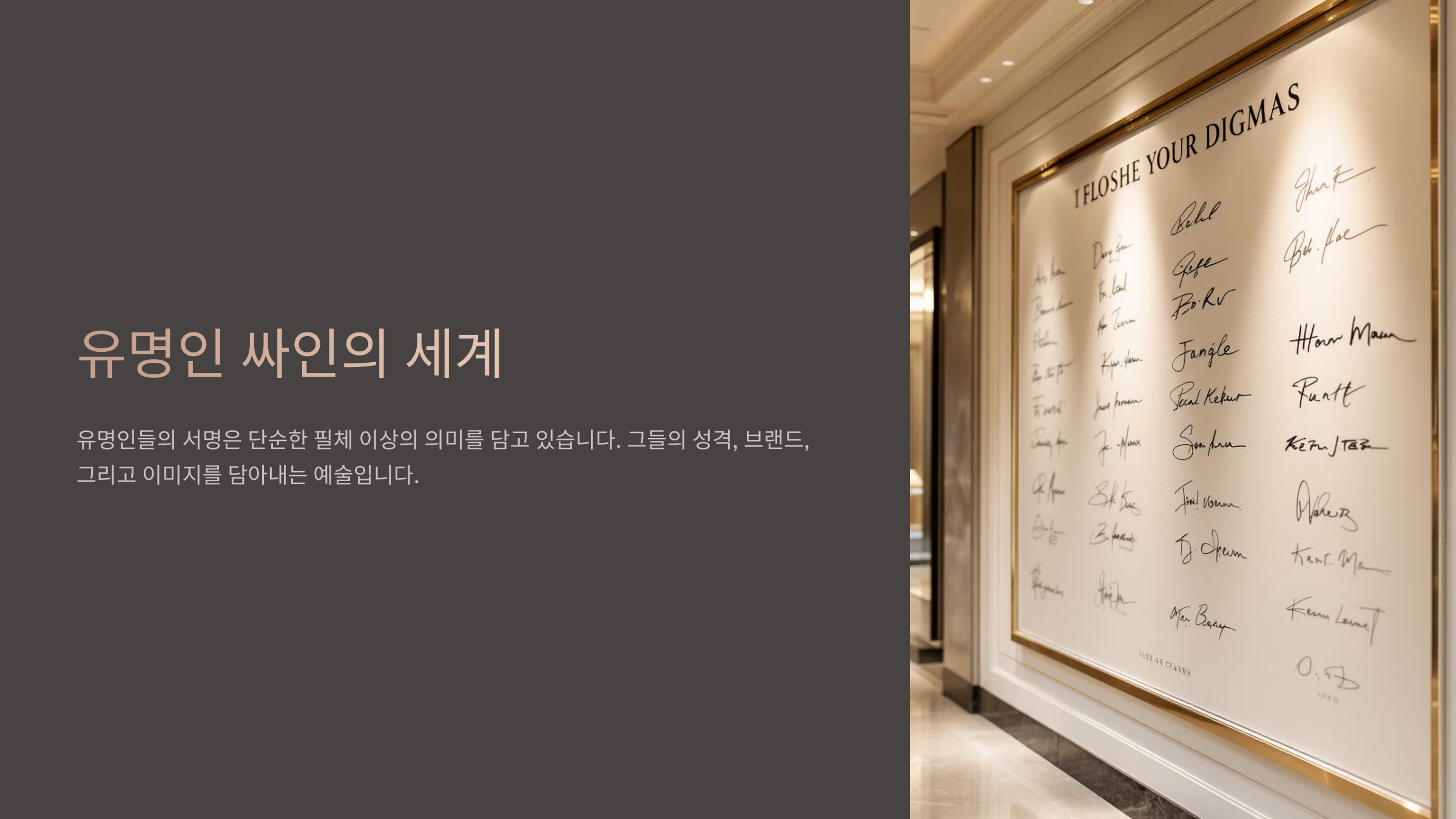
예를 들어, 빌 게이츠, 스티브 잡스, 일론 머스크 같은 CEO들의 싸인은 비즈니스적인 신뢰감을 주고, 유명 연예인들의 싸인은 개성 넘치는 스타일을 보여줘요. 이제 유명인들의 싸인을 분석하고, 나만의 스타일을 만드는 방법을 알아볼까요? 🔥
유명인 싸인을 참고하는 이유 🌟
유명인의 싸인은 단순한 서명이 아니라 그들의 브랜드와 개성을 담고 있는 요소예요. 그렇기 때문에 싸인을 연구하면 멋진 스타일을 만들고, 나만의 개성을 살릴 수 있어요! ✍️유명인의 싸인을 참고하는 이유는 다음과 같아요:
📌 유명인 싸인 참고의 장점 ✅
이유 설명 1. 개성 표현 유명인의 싸인은 강한 인상을 주는 요소가 많음 2. 브랜드 이미지 구축 CEO나 연예인의 싸인은 브랜드와 연결됨 3. 필기체 연구 다양한 필기체 스타일을 배울 수 있음 4. 간결함과 가독성 읽기 쉬우면서도 멋진 싸인 제작 가능 유명인의 싸인을 보면 싸인의 흐름, 스타일, 개성을 배울 수 있어요! 그럼 이제, 유명 CEO들의 싸인 스타일을 분석해 볼까요? 💼
유명 CEO들의 싸인 스타일 💼
세계적인 기업 CEO들의 싸인은 비즈니스적 신뢰감과 권위를 나타내는 요소예요. 그들의 싸인을 분석하면 깔끔하고 프로페셔널한 싸인 스타일을 배울 수 있어요! ✍️
📌 유명 CEO 싸인 스타일 분석 ✅
CEO 싸인 특징 스타일 빌 게이츠 (Bill Gates) 이니셜을 강조하며 깔끔한 필기체 "B. Gates" 스티브 잡스 (Steve Jobs) 독특한 필체와 흐름이 있는 곡선 "Steve Jobs" (곡선 강조) 일론 머스크 (Elon Musk) 빠르고 역동적인 스타일 "E. Musk" (속도감 강조) 제프 베이조스 (Jeff Bezos) 부드러운 필기체로 자연스러운 흐름 "J. Bezos" CEO들의 싸인은 명확하고 깔끔하면서도, 속도감과 개성이 반영된 스타일이 많아요. 그럼 이제, 연예인과 스포츠 스타들의 싸인은 어떤 특징이 있는지 살펴볼까요? 🎤⚽
연예인과 스포츠 스타들의 싸인 특징 🎤⚽
연예인과 스포츠 스타들의 싸인은 팬들에게 강한 인상을 남기고, 브랜드 이미지를 형성하는 요소예요. 이들의 싸인은 개성이 강하고 예술적인 느낌이 많으며, 종종 독창적인 심볼이 포함되기도 해요. ✍️
📌 유명 연예인 & 스포츠 스타 싸인 스타일 ✅
유명인 싸인 특징 스타일 마이클 잭슨 (Michael Jackson) 길게 늘어진 곡선과 리드미컬한 흐름 "M. Jackson" (유연한 곡선 강조) 비욘세 (Beyoncé) 스타일리시한 필기체와 끝에 별 장식 "Beyoncé ✨" 리오넬 메시 (Lionel Messi) 짧고 강렬한 획, 간결한 이니셜 "L. Messi" 크리스티아누 호날두 (Cristiano Ronaldo) 속도감 있는 강렬한 획과 강조된 C.R "C.Ronaldo ⚡" 연예인과 스포츠 스타들은 팬들에게 각인될 수 있도록 독창적이고 강한 스타일을 많이 사용해요. 그럼 이제, 정치인과 역사적 인물들의 싸인은 어떤 특징이 있는지 분석해볼까요? 🏛️
정치인과 역사적 인물의 싸인 분석 🏛️
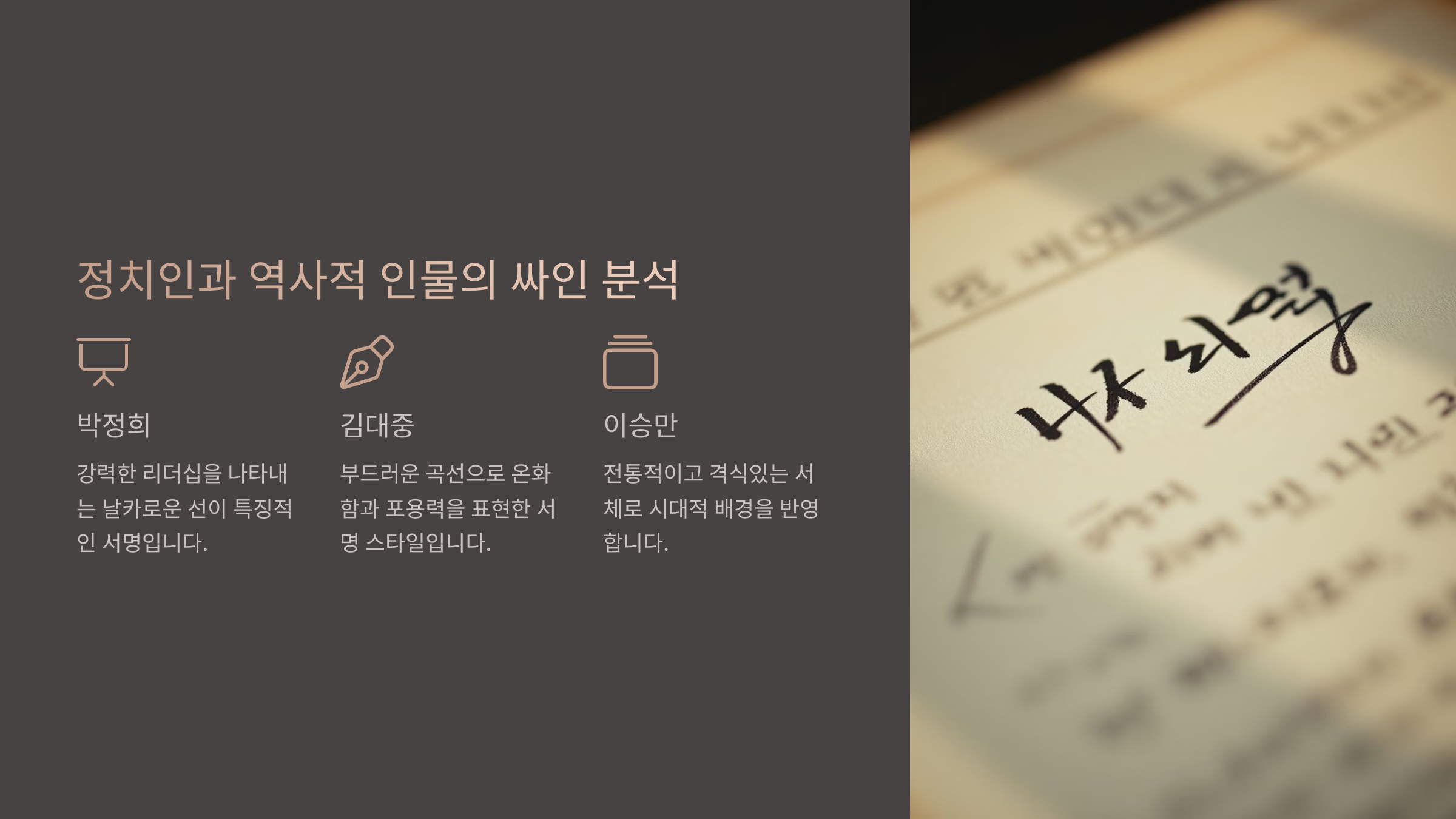
정치인과 역사적 인물들의 싸인은 권위, 신뢰, 리더십을 상징하는 요소예요. 이들의 싸인은 종종 강한 필압과 명확한 획이 특징이며, 공식 문서에서 많이 사용되죠. ✍️
📌 유명 정치인 & 역사적 인물의 싸인 스타일 ✅
인물 싸인 특징 스타일 조지 워싱턴 (George Washington) 정확하고 대칭적인 글씨체, 강한 필압 "G. Washington" 윈스턴 처칠 (Winston Churchill) 유려한 곡선과 독특한 필기체 "W. Churchill" 존 F. 케네디 (John F. Kennedy) 빠르고 자연스러운 흐름, 가독성 높은 필체 "J.F.K." 넬슨 만델라 (Nelson Mandela) 부드럽고 자연스러운 필기체, 연결된 획 "N. Mandela" 정치인과 역사적 인물들의 싸인은 위엄과 권위를 강조하는 요소가 많아요. 그럼 이제, 유명인의 싸인에서 우리가 배울 점을 정리해볼까요? ✨
유명인 싸인에서 배울 점 ✨
유명인의 싸인을 분석하면 어떤 요소가 멋진 싸인을 만드는지 배울 수 있어요. 단순히 따라 하는 것이 아니라, 핵심적인 스타일을 참고해 나만의 싸인을 만들어야 해요! ✍️
📌 유명인 싸인의 핵심 요소 ✅
요소 설명 예시 1. 간결함 읽기 쉽고 빠르게 쓸 수 있도록 단순한 스타일 유지 "J.K." / "H. Park" 2. 독창성 이름의 특정 글자를 강조하거나 특수 기호 활용 "M. Lee ✨" / "S. Lim ★" 3. 흐름 끊기지 않고 부드럽게 이어지는 필기체 활용 "Beyoncé" (유려한 곡선) 4. 속도감 빠르게 쓰면서도 형태가 유지되는 스타일 "E. Musk" (강한 획) 이제 유명인의 싸인에서 배운 요소들을 활용해 나만의 싸인 스타일을 만들어볼 차례예요! 🔥
나만의 싸인 스타일 만들기 ✍️
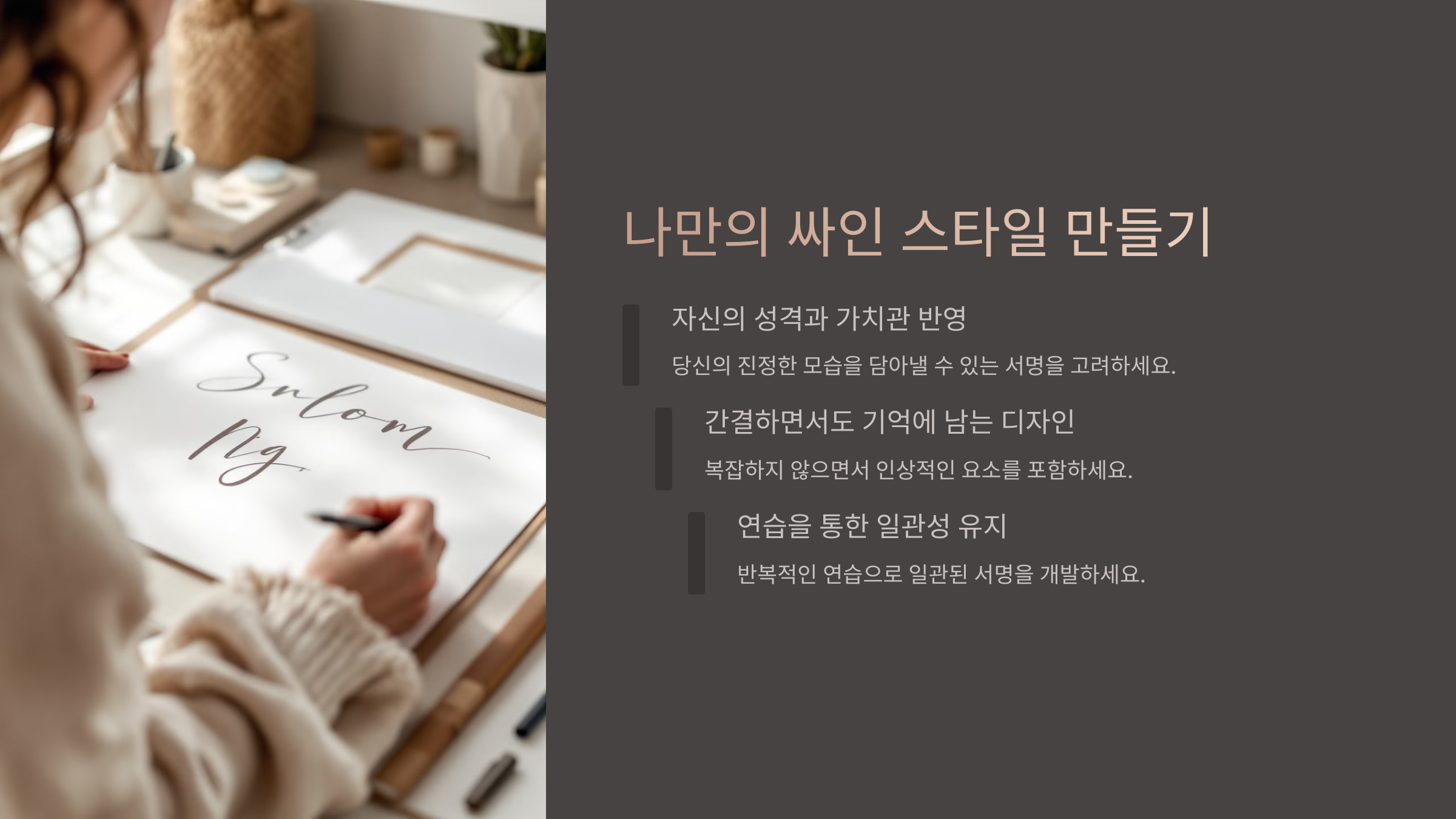
유명인의 싸인을 참고했다면, 이제 나만의 개성을 담은 싸인을 만들어볼 차례예요. 단순히 따라 하는 것이 아니라, 자신의 이름과 스타일을 반영해야 해요. ✅
📌 나만의 싸인 스타일을 만드는 5단계 🚀
단계 설명 1. 기본 형태 정하기 이름을 풀네임으로 쓸지, 이니셜을 활용할지 결정 2. 필기체 스타일 선택 부드러운 곡선, 직선, 속도감 있는 획 중 선택 3. 디테일 추가 밑줄, 점, 별 등 자신만의 개성을 더할 요소 정하기 4. 반복 연습 적어도 100번 이상 싸인을 연습하며 손에 익히기 5. 실전 적용 계약서, 메모 등에 실제로 싸인을 사용해보기 이제 나만의 싸인을 완성했다면, 싸인과 관련된 자주 묻는 질문(FAQ)을 정리해볼게요! 📢
FAQ
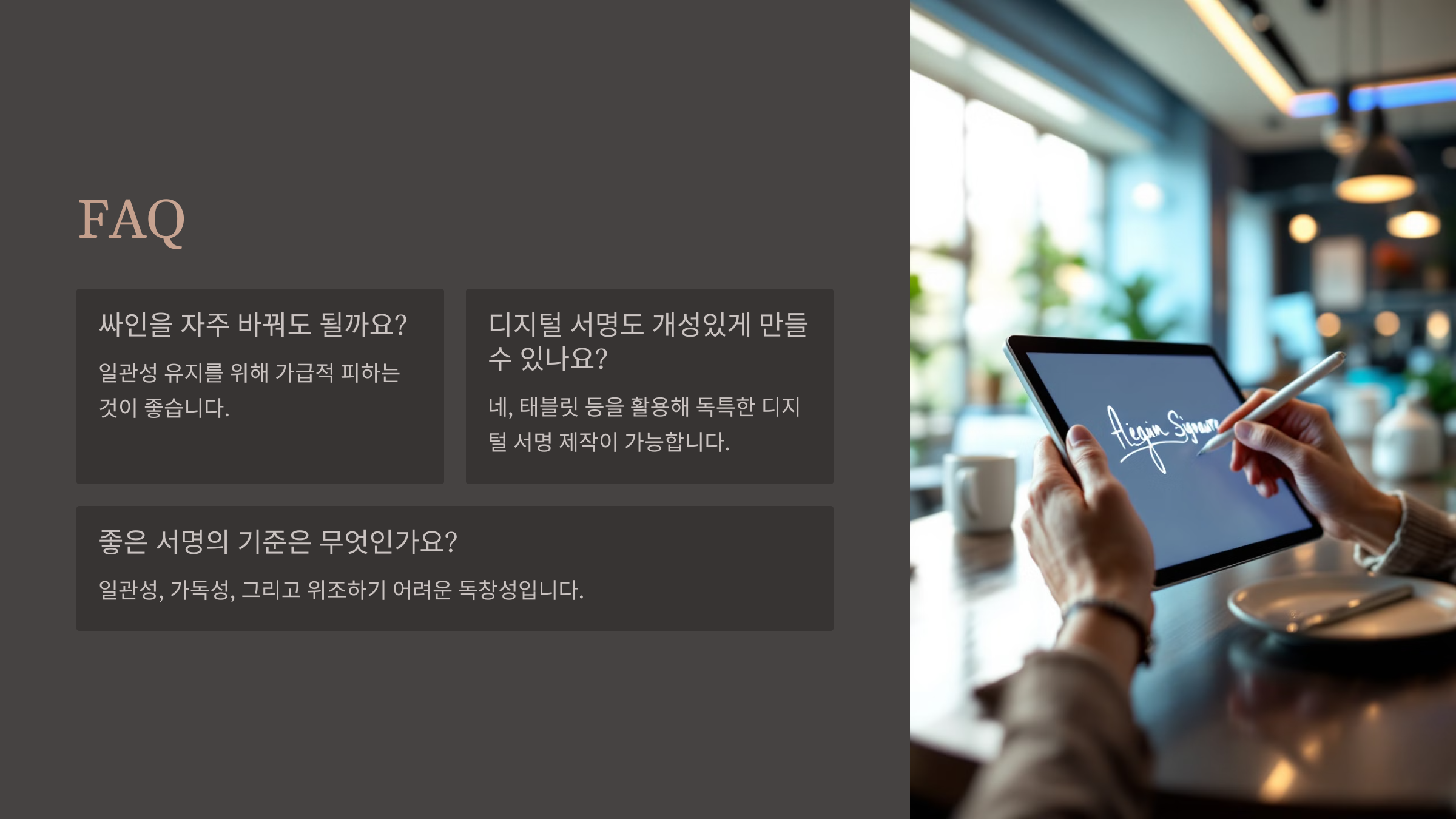
Q1. 싸인을 만들 때 가장 중요한 요소는?
A1. 가독성과 개성을 동시에 고려해야 해요. 너무 단순하면 흔해 보이고, 너무 복잡하면 실용성이 떨어질 수 있어요. ✨
Q2. 싸인을 더 멋지게 보이게 하는 방법이 있나요?
A2. 이니셜을 강조하거나, 곡선과 직선을 조합하는 것이 좋아요. 또한, 특수 기호(밑줄, 점, 별 등)를 추가하면 더욱 멋져 보여요! ⭐
Q3. 싸인을 빠르게 연습하는 방법이 있나요?
A3. 천천히 연습한 후 점점 속도를 높이는 방식이 좋아요. 또한, 같은 스타일을 반복 연습하면 손에 익숙해져요. 🖊️
Q4. 싸인을 자주 바꿔도 되나요?
A4. 비공식적인 싸인은 변경 가능하지만, 공식적인 문서에서 사용하는 싸인은 일관성을 유지하는 것이 좋아요. 📄
Q5. 유명인의 싸인을 참고해도 되나요?
A5. 네! 빌 게이츠, 스티브 잡스, 일론 머스크 등의 싸인을 참고하면 싸인의 스타일과 균형을 배우는 데 도움이 돼요. 하지만 자신만의 개성을 추가하는 것이 중요해요! 🏆
Q6. 싸인을 꾸준히 연습하는 방법은?
A6. 하루 5분씩 짧게라도 반복해서 연습하는 것이 효과적이에요. 싸인을 녹화하거나, 다양한 필기구를 사용해 보면 스타일을 더 빨리 확립할 수 있어요! 🚀
Q7. 싸인을 빠르게 하려면 어떻게 연습해야 하나요?
A7. 처음에는 천천히 연습한 후 점점 속도를 높이는 방식이 좋아요. 손목과 손가락을 유연하게 풀어주면 속도감 있는 싸인을 만들 수 있어요. 💨
Q8. 싸인에도 법적 효력이 있나요?
A8. 네! 계약서나 공식 문서에서 사용되는 싸인은 법적으로 중요한 역할을 해요. 따라서 일관된 싸인을 유지하는 것이 중요해요. ⚖️